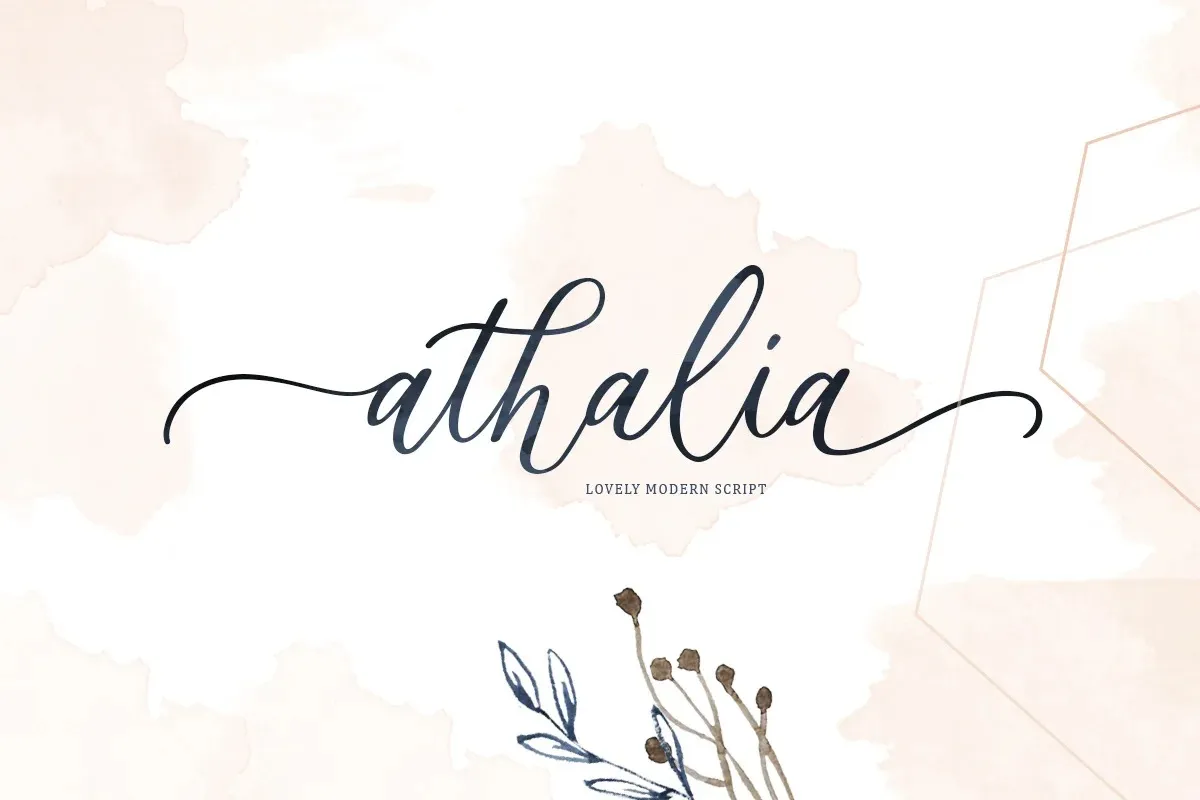
A Athalia Font é uma elegante tipografia aquarelada criada pela Letterhend Studio. Ela oferece uma sensação vibrante e fresca que combina bem com qualquer projeto moderno, especialmente para aplicações como headlines, logotipos, roupas, cartões de convite, marcação, embalagens e publicidade. Este font é perfeitamente adaptado tanto para letras maiúsculas quanto minúsculas, incluindo sinais, símbolos e números. Além disso, a Athalia Font inclui um conjunto alternativo estilizado, ligações personalizadas e suporte para múltiplas línguas, tornando-a uma fonte versátil e adaptável para um amplo espectro de aplicações gráficas. Seja você designer ou tipógrafo, a Athalia Font é certamente o tipo certo para seus projetos criativos.